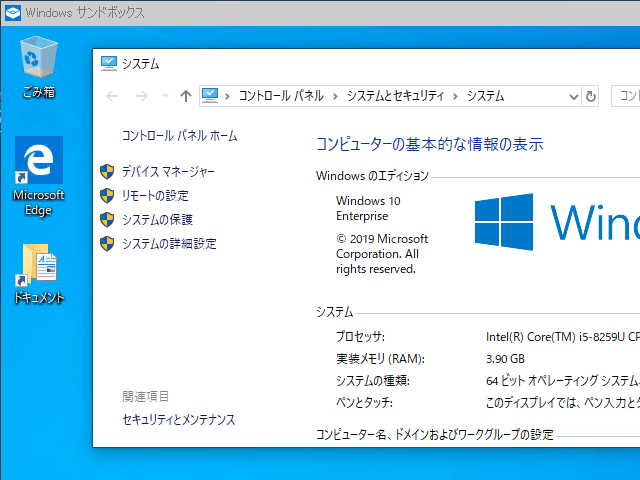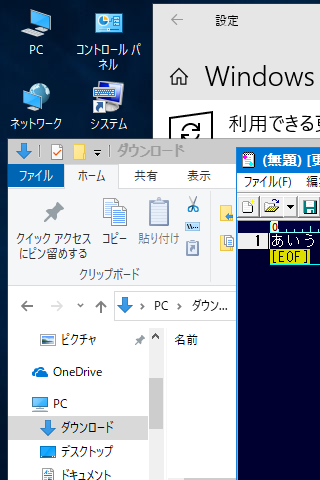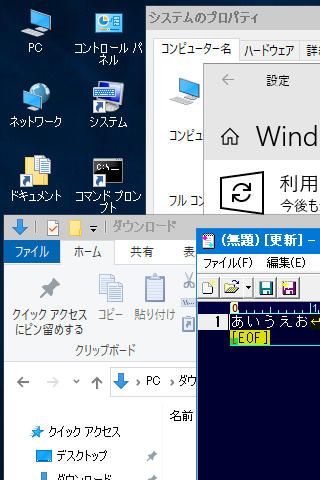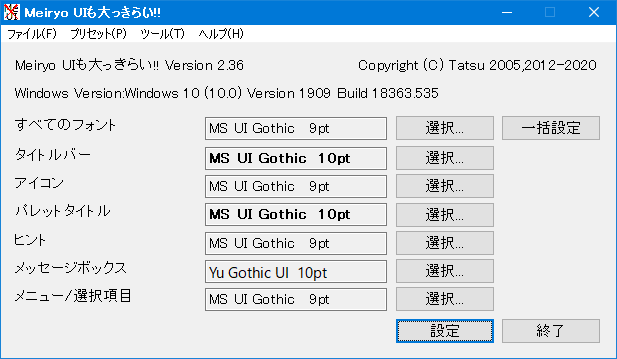
Windows 10の汚いにじむ文字テキストのフォントをクッキリ見易く奇麗なシステムフォントに変更する方法
(Windows 10のシステムフォントを遊ゴシックからクッキリの MS UI Gothicフォントに変更する方法)
● Windows 10の汚いにじむ文字テキストのフォントをクッキリ見易く奇麗なシステムフォントに変更する方法
Windows 10のシステムフォントを遊ゴシックから MS UI Gothicフォントに変更する方法。
Clear Typeテキスト以前の問題。
● Windows 10のシステムフォントをクッキリ見易いフォントに変更する方法
Windows 10のシステムフォントを遊ゴシックから MS UI Gothicフォントに変更する方法。
MS UI Gothicフォントは Windows XPで使用のシステムフォントです。
●遊ゴシック
・遊ゴシック
● MS UI Gothic
・MS UI Gothic
●遊ゴシック
・遊ゴシック
● MS UI Gothic
・MS UI Gothic
● Windows 10のシステムフォントをクッキリ見易いフォントに変更する方法
上記のプログラムは「MeiryoUIも大っきらい!!」のアプリの下記の設定に相当します。
MeiryoUIも大っきらい!!
・MeiryoUIも大っきらい!!での設定相当